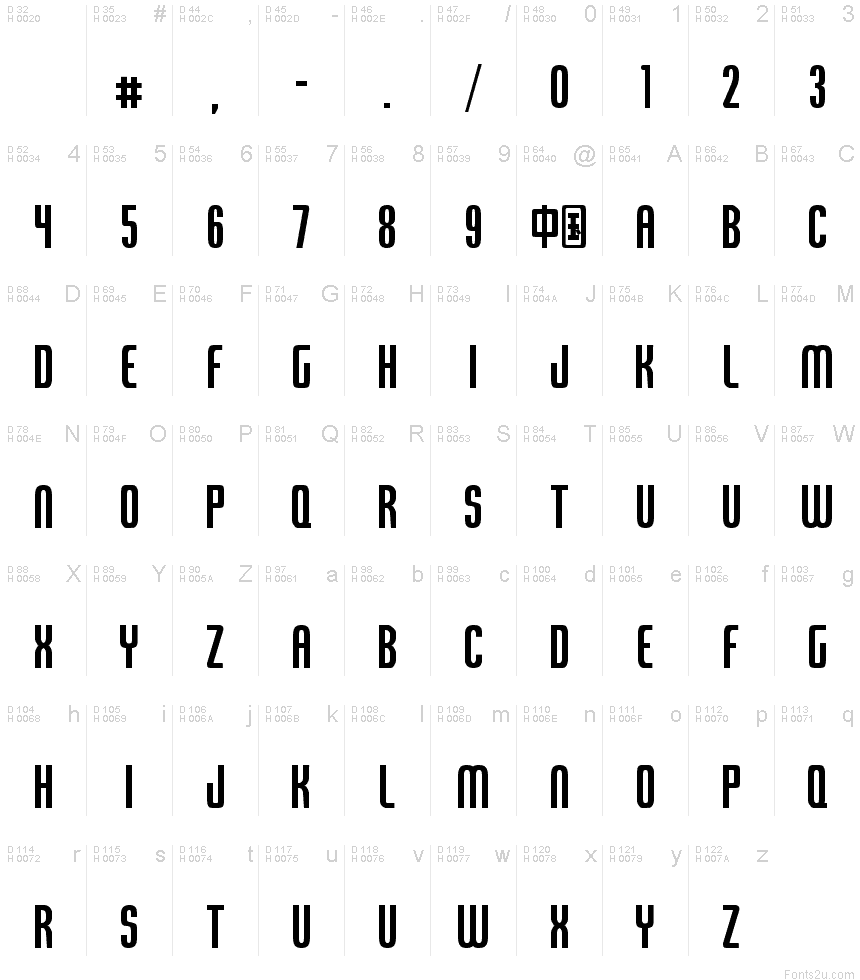
Tangerine XCn Tim2
Tangerine XCn Tim2, od Timoura Jgentiho z Lucifer Vision, je moderní, bezplatný a zúžený displejový font s cool nádechem módy konce 20. století. Písmena jsou vysoká a těsně vykreslená, s vnějšími zaoblenými rohy a širokými křivkami, které kontrastují s rovnými svislými stranami. To dodává písmu elegantní rytmus, který působí městsky a lehce retro.
Přirozeně se hodí na plakáty, klubové letáky, titulky časopisů, karty s názvy a značkové wordmarky, kde úzká písmena pomáhají udržet výšku, aniž by zabírala příliš mnoho místa na šířku. Jako bezplatný font funguje obzvlášť dobře pro krátké nadpisy a monogramy, protože tyto protáhlé tvary a měkké rohy dodávají i několika písmenům výraznou siluetu.